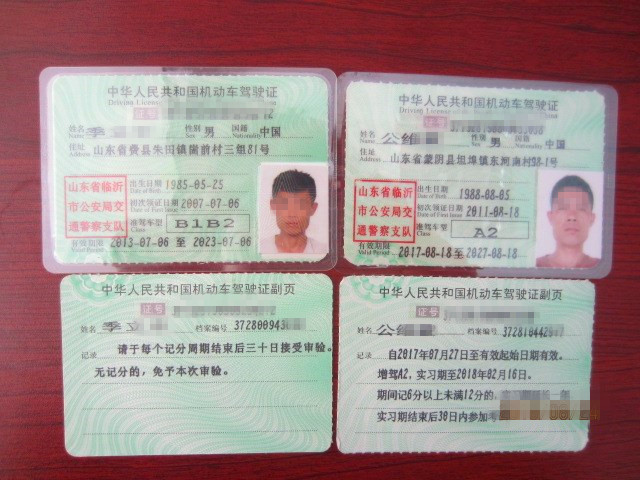
小小字体藏玄机 民警慧眼识假证
大众网日照8月29日讯(通讯员 贺超)8月28日17时50分许,日照港港航公安局岚山港区分局执勤民警路面执勤时,对号牌为鲁Q5XXX/鲁QAXXX挂的重型半挂车例行检查,发现该车驾驶员出示的驾驶证字体明显有别于常见的驾驶证,驾驶证为特殊专用字体而该驾驶员出示的驾驶证为普通打印字体;民警遂对驾驶员进行现场询问,发现驾驶员并不能说出该驾驶证的驾驶证号等信息;在进一步通过“手持终端”对驾驶员进行信息比对,查出驾驶员真实姓名季某,而其出示的驾驶证为公某,其驾驶证涉嫌伪造,且季某的准驾车型为B1B2,不能驾驶重型半挂车辆,涉嫌使用伪造的机动车驾驶证、驾与准驾车型不符的违法行为。